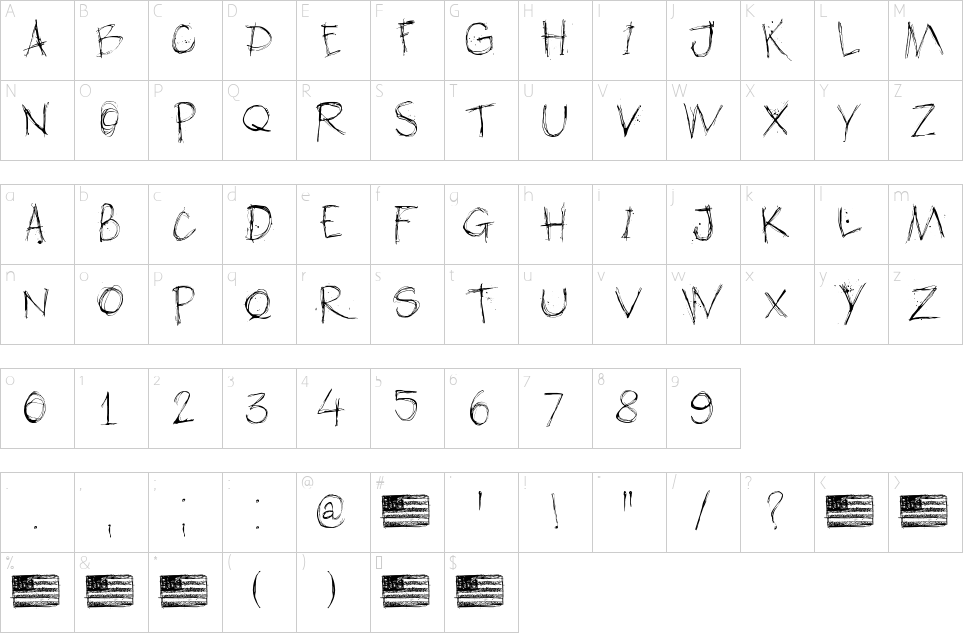
DK American Grunge Font – Fonte Grátis
DK American Grunge Font
DK American Grunge é uma fonte única e distinta que traz consigo a essência dos anos 90 e suas influências contemporâneas. Especialmente popular entre os amantes da cultura grunge, esta fonte evoca memórias de letras abertas e linhas robustas, perfeita para aplicar um toque nostálgico em designs criativos ou uma atmosfera rebelde em projetos visuais. Desenvolvida por Hanoded, DK American Grunge foi descarregada centenas de vezes, demonstrando sua relevância e popularidade entre designers gráficos. Adquira agora esta fonte gratuita para Windows e Mac, perfeita para criar trabalhos que combinam elegância com energia rebelde no design digital.